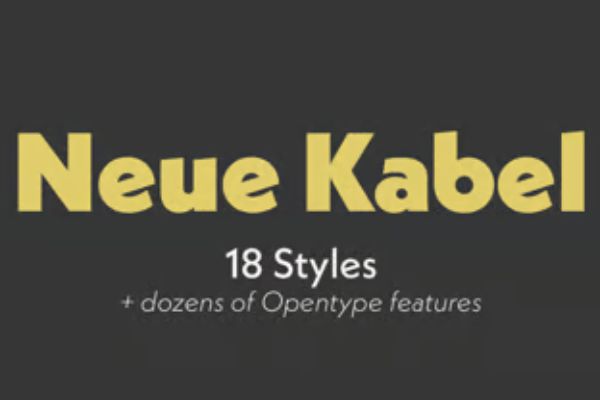
Neue Kabel® Pro Light
Neue Kabel 更新和重新塑造了原始 Kabel 字体,保持了其风格和活力,创造在现代应用环境中表现良好的形式。Neue Kabel 能够满足最苛刻的现代排版应用需求,在各种印刷和数字环境中表现出了出色的多功能性,也为创建个人和企业 logo 提供了多种可能性。Neue Kabel 支持大多数中欧和许多东欧语言的扩展字符集。